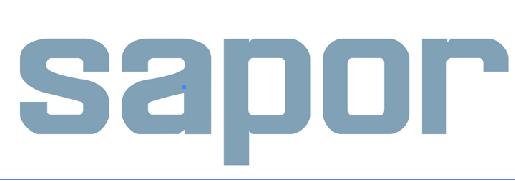
Welche Schrift könnte das sein?
Auf den ersten Blick schaut die schon wirklich sehr zusammengebastelt aus. Hast du da noch mehr davon, oder ein PDF, in dem sie (als Text) verwendet wird?
Ist das Beispiel in der Höhe etwas gestaucht? Das Original sieht ja so aus: